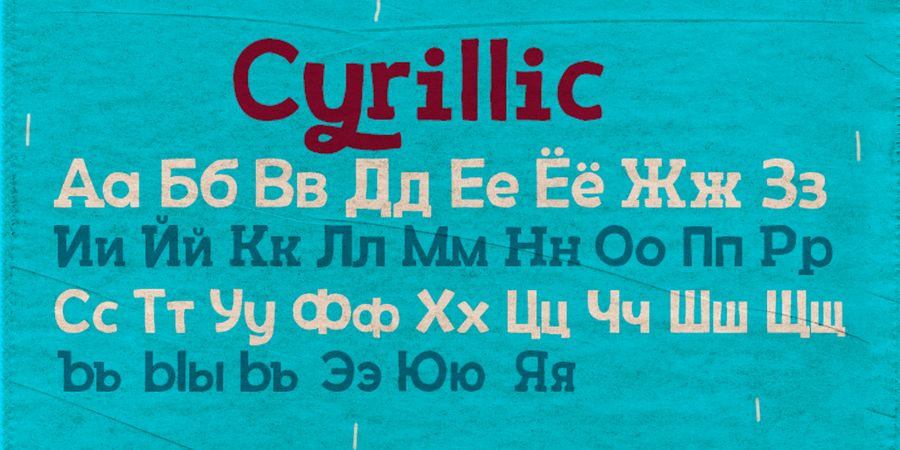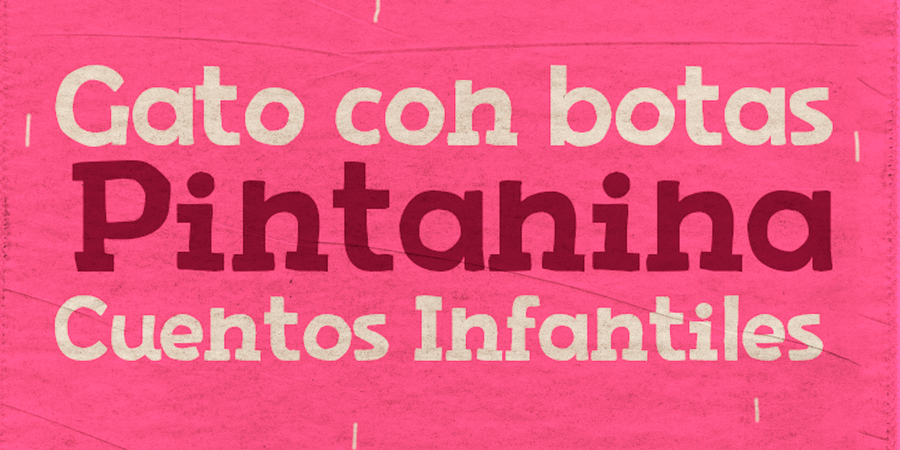
Шрифтова пара з Stolzl Text Book (1 з 5)Опис шрифта MartyМарті – неформальний мальований брусковий шрифт з грайливим хлоп'ячим настроєм. Він підтримує безліч європейських мов, а також кирилицю. Цей шрифт має величезні можливості у вигляді альтернативних гліфів, розчерків та рідкісних лігатур. Шрифт Марті розробив Родріго Арая Салас у 2014 році.
Особливості сімейства шрифтів MartyХіт десятиліття:
стінгазета, журнал, комікс, пакування, листівка, анімація, мультфільм, вивіска, обкладинка, плакат, реклама, етикетка, афіша, меню, відео, шкільна дошка, стікер, наліпка Адаптованість гарнітури до носіїв:
Асоціації з сімейством шрифтів MartyОсобистість і характер гарнітури:
вуличний, міський, крафтовий, неформальний, мультяшний, ручний, рукотворний, кустарний, саморобний, живий, ламповий, помітний, виразний, неохайний, ремісничий, потішний, іронічний, міцний, здоровий, бадьорий, сильний, сільський, старомодний, ковбойський, мачо, фермерський, веселий, смішний, доброзичливий, добродушний, добрий, грайливий, рухливий, свіжий, стиглий, смачний, важкий, дитячий, наївний, карикатурний, милий, дотепний, літній, щасливий, грубий, оригінальний, характерний, неотесаний, нерівний, гулящий, дозвільний, пещений, незграбний, круглий, щедрий, цікавий, дерев'яний, прямокутний, квадратний, студентськиий, тусовочний, прикольний, творчий, симпатичний, артізанальний, недбалий, вернакулярний, ігровий, хлоп'ячий, нервовий
дача, хенд мейд, відпочинок, природа, анімація, мультфільм, закуска, фаст фуд, торгівля, крамниця, школа, щоденник, Місто, графіті, магазин, гра, одяг, взуття, їжа, м'ясо, ферма, джинси, ранчо, трактир, ковбой, обід, вечеря, гамбургер, канцтовари, сніданок, гумор, табір, гурток, олівці, іграшка, дитяча книжка, розфарбування, спеції, зошит, конструктор, пригоди, кубики, розваги, вечірка, канікули, лего, графіка, ілюстрація, учень, школяр, ранок Гарнітура асоціюється з віком: